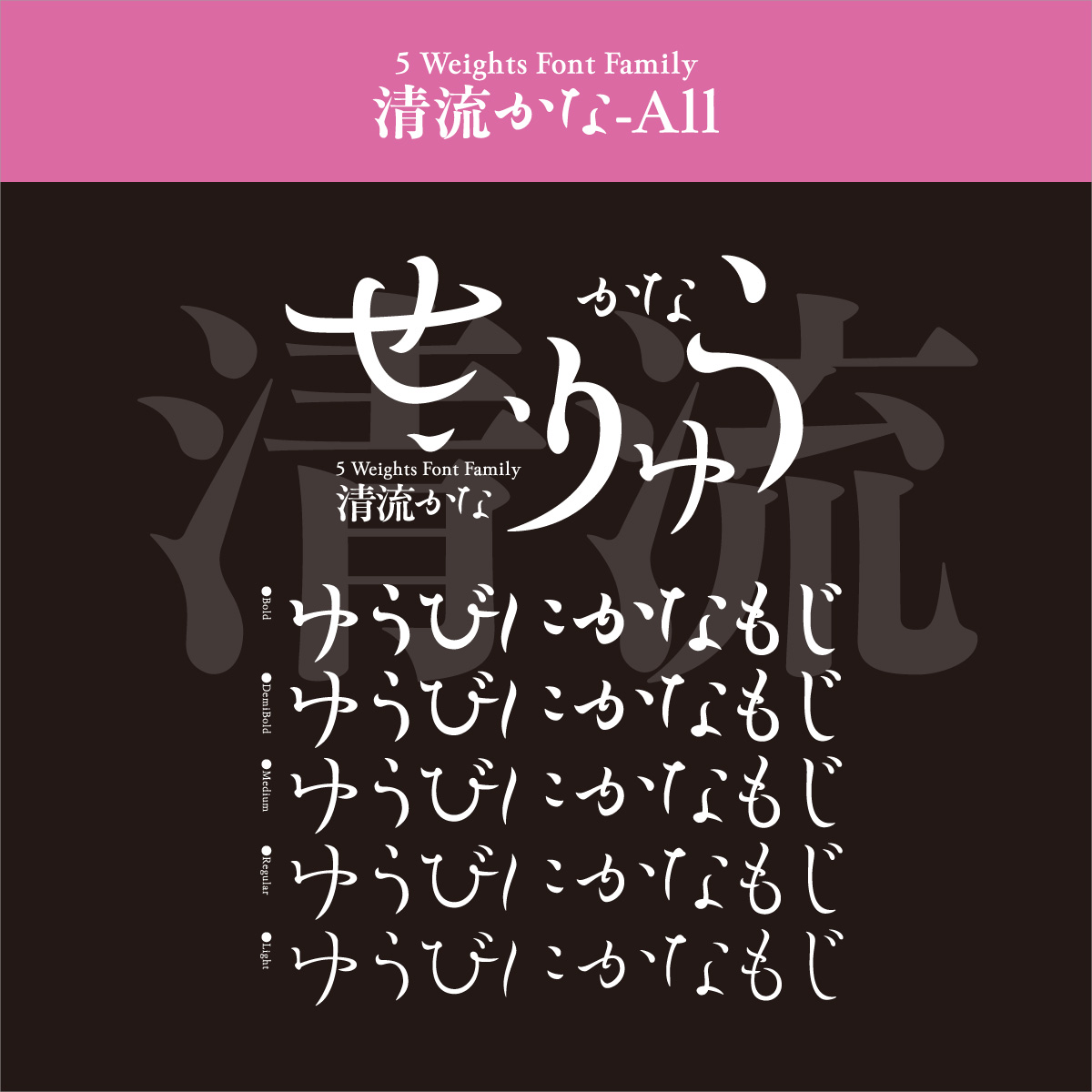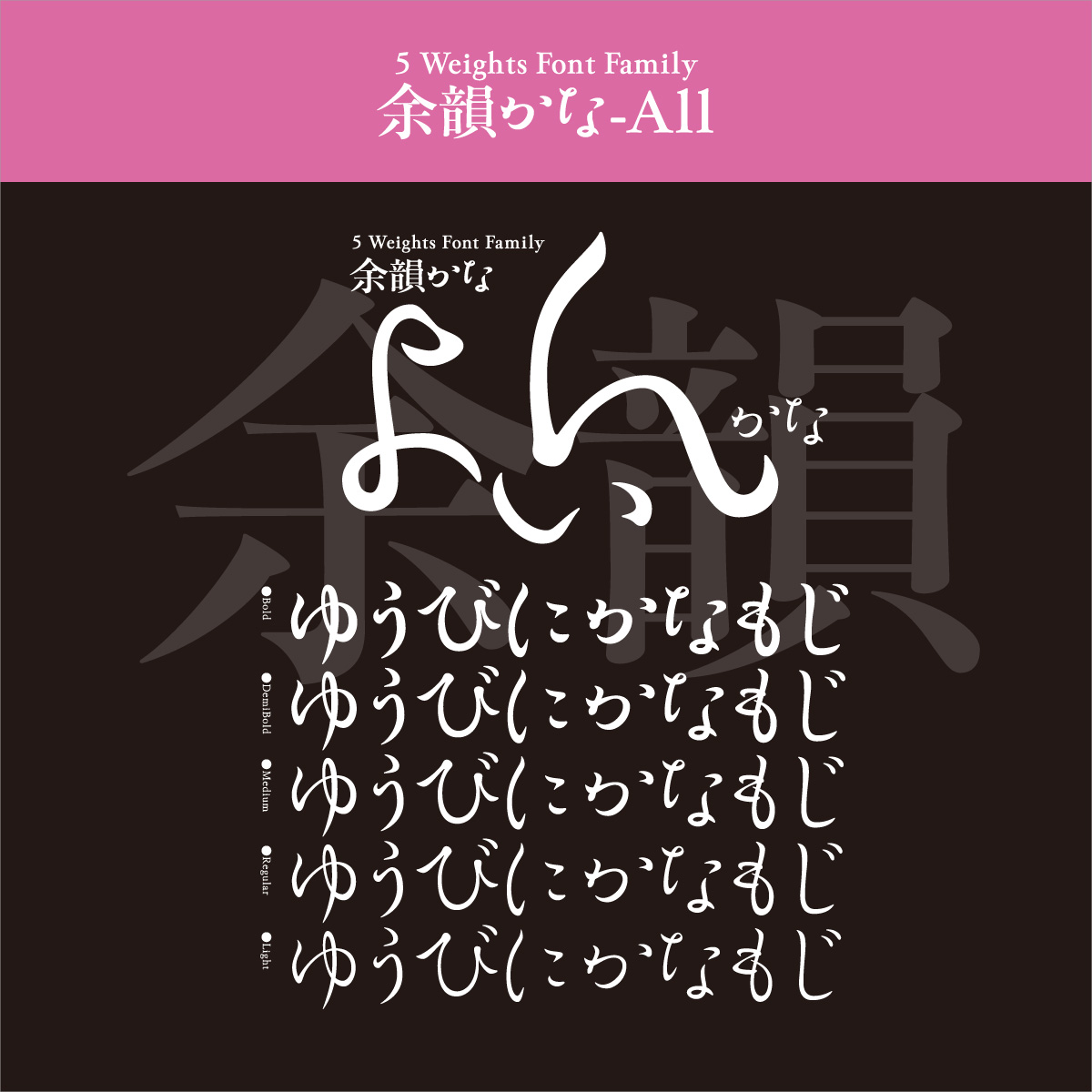
書体デザイナー REN FONT 日本のタイプファウンダリー プロフィール NPO法人日本タイポグラフィ協会主催の作品展「年鑑」のタイプフェイス部門で入選を重ね、着実に実績を積んできたREN FONT。フォント業界に新風を送るべく2001年に設立。 REN FONTのタイプデザイナー・金井和夫が創り出す手書き風フォントは、プロのデザイナー・タイポグラファーから高い評価を得ています。 さらに詳しく閉じる 代表フォント 制作フォント Can't login